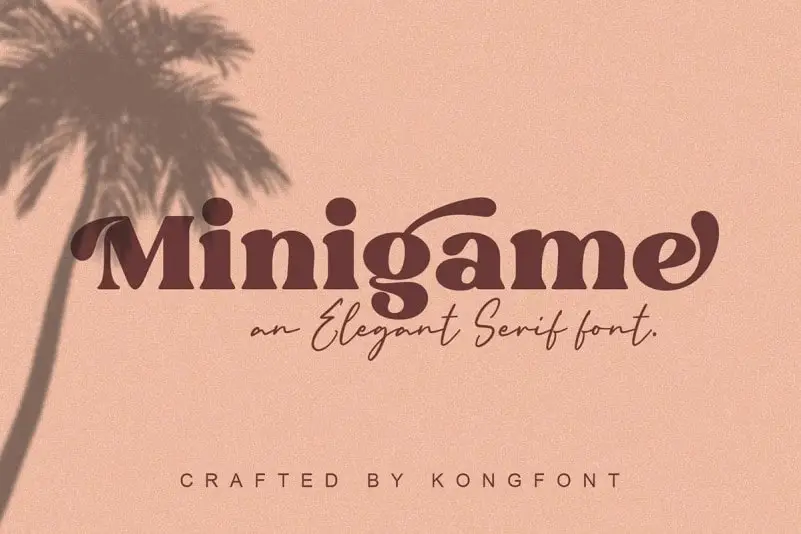
A Minigame Serif Font é uma fonte serif moderna com contornos afiados que preservam a elegância dos serifos clássicos. Criada pelo designer font Kong Font, essa fonte possui um estilo serifa leve e divertido, incorporando alternativas e ligaturas para criar estilos de logotipos impressionantes, citações, postagens do blog, projetos de marca, imagens de revistas e até cartões de casamento. Ideal para designers em busca de uma tipografia que se adapte perfeitamente a uma ampla gama de usos gráficos. Atrairá qualquer designer desejando adicionar um toque elegante e moderno a seus projetos.